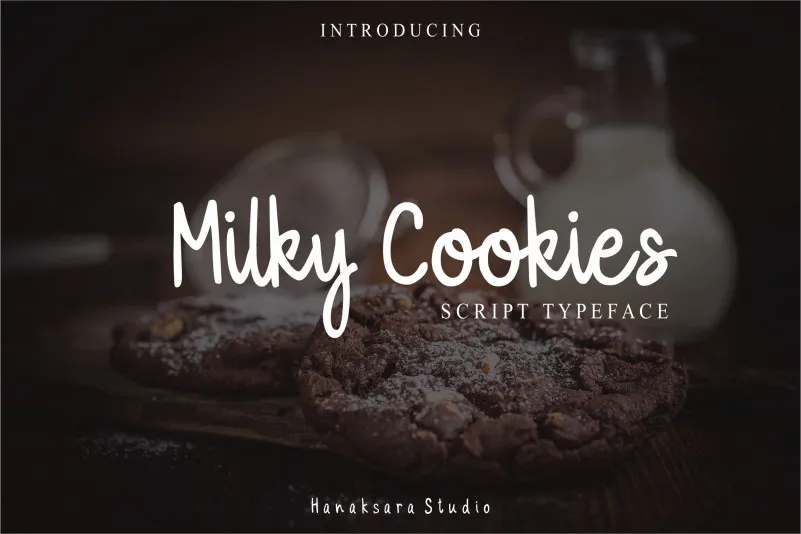
Milky Cookies Typeface – Download Grátis
A Milky Cookies Typeface é uma elegante fonte escrita a mão que oferece um toque delicado e acolhedor. Suas linhas suaves e os traços leves criam um design fluido e envolvente, tornando-a perfeita para aplicar em variados ambientes de negócios, como o logotipo de uma cafeteira ou um cardápio de restaurante. Seu charme não pára por aí; ela também atende perfeitamente aos desafios do design de capa de livros e dos títulos das blogs, oferecendo uma textura única que cria uma conexão imediata com o leitor. Com sua aparência amigável e harmoniosa, Milky Cookies é uma escolha ideal para quem busca um toque delicado em qualquer projeto gráfico.
Designer: Hanaksara.Studio